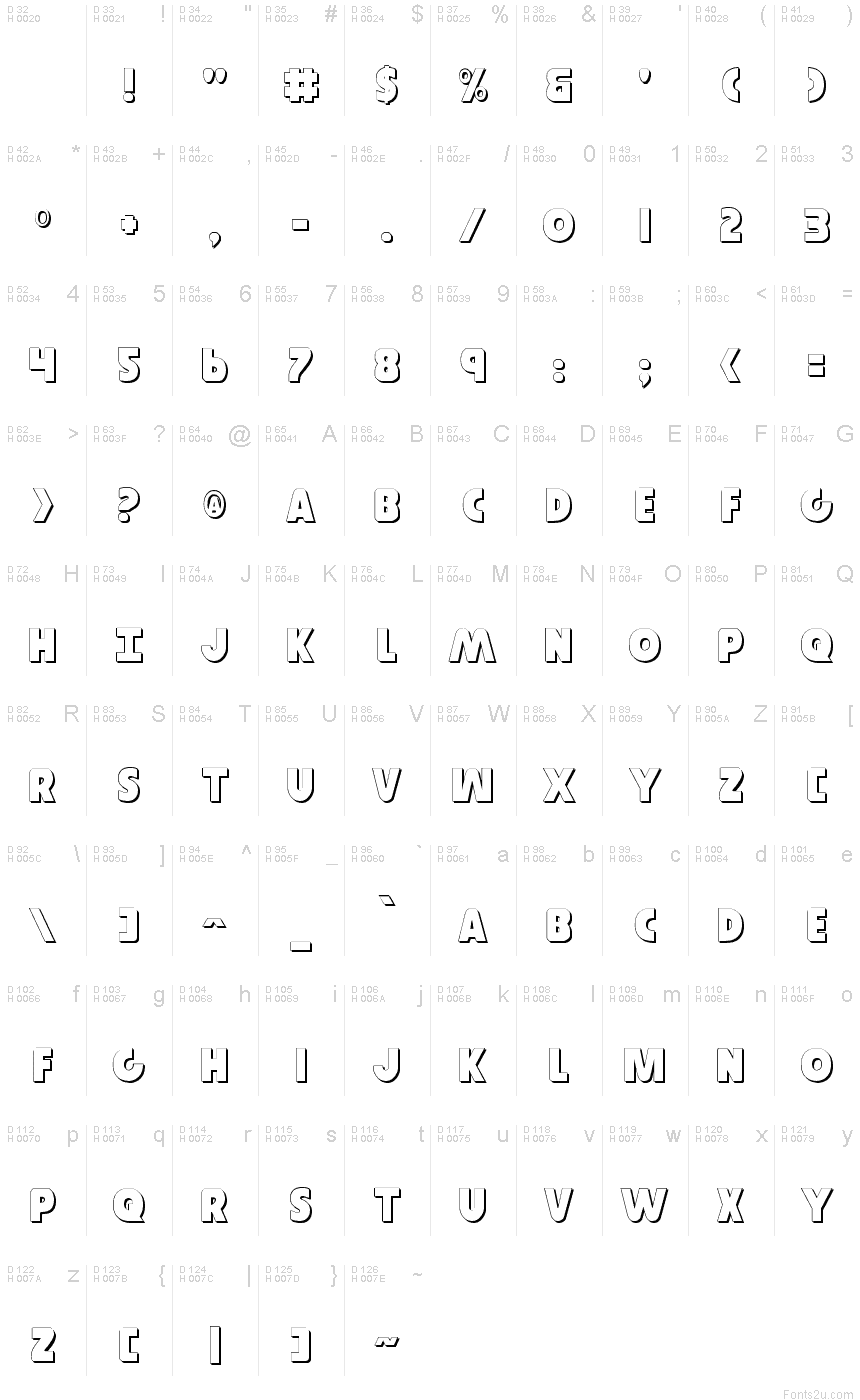
Governor Shadow von Iconian Fonts ist eine moderne, kostenlose Display-Schrift, die mit kräftigen, selbstbewussten Formen und einer spielerischen Note überzeugt. Die voluminösen, abgerundeten Buchstaben mit ihren fetten schwarzen Konturen und einem scharfen Offset-Schatten lassen jedes Wort fast wie einen Aufkleber hervorstechen. Der Look ist laut, aber freundlich – eine Mischung aus klassischen handgemalten Ladenschildern und Cartoons am Samstagmorgen.
Mit Governor Shadow ziehen Überschriften selbst aus der Ferne alle Blicke auf sich. Das macht die Schrift perfekt für Poster, Spieletitel, Comic-Cover, Produkte für Kinder, Flyer und plakative Social-Media-Grafiken. Dieser kostenlose Font glänzt vor allem in großen Größen. Kombinieren Sie ihn in kleineren Textpassagen mit einer klaren, geometrischen serifenlosen Schrift, um die Lesbarkeit des Layouts zu gewährleisten, während die schattierten Buchstaben für das visuelle Highlight sorgen.